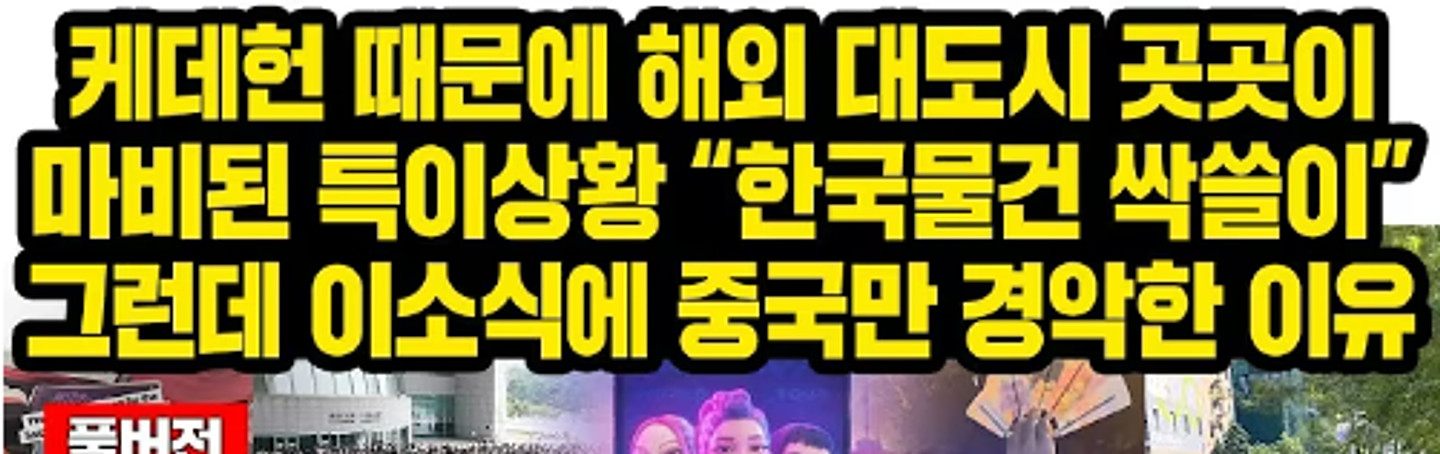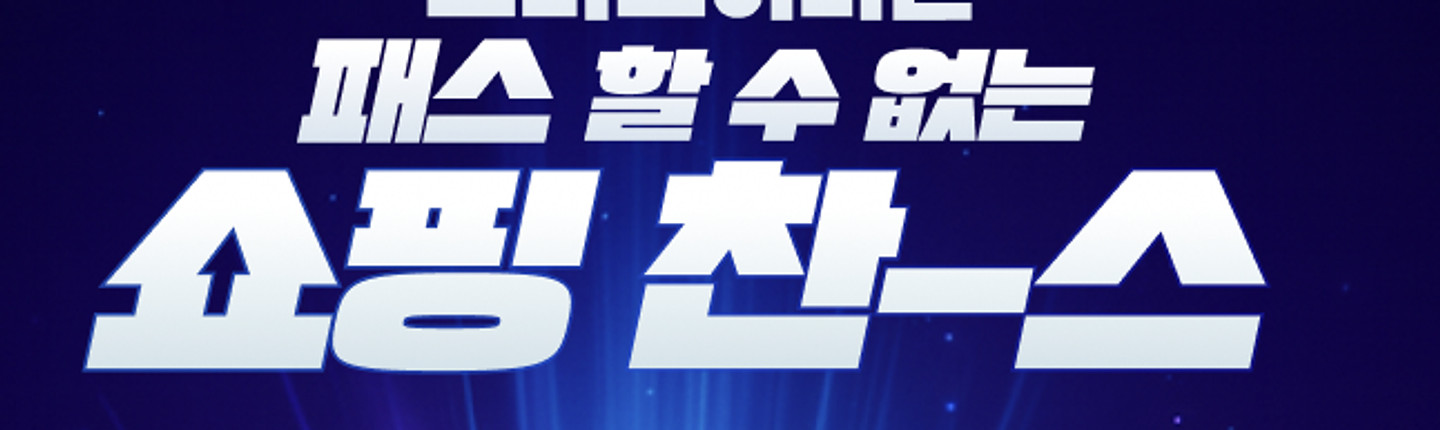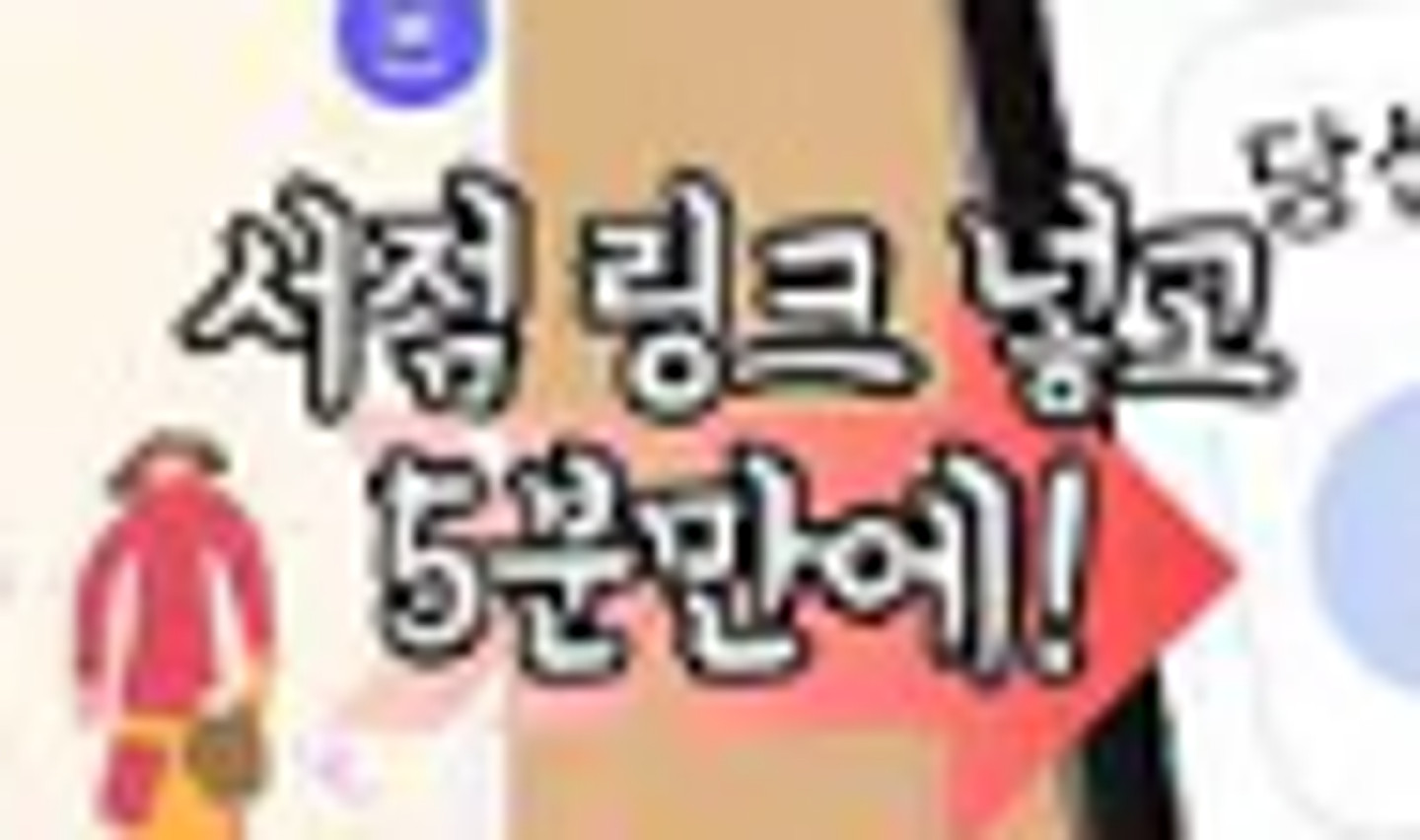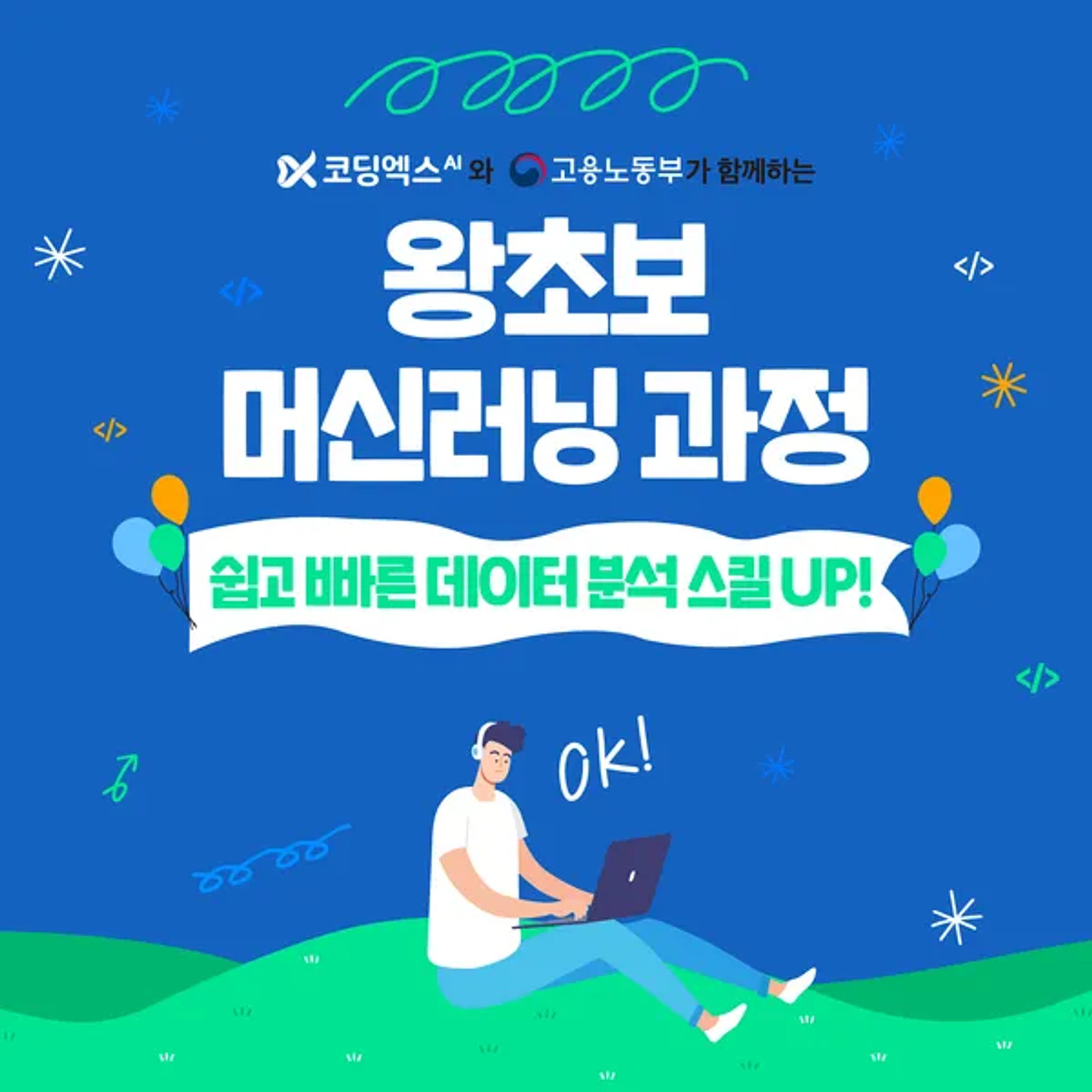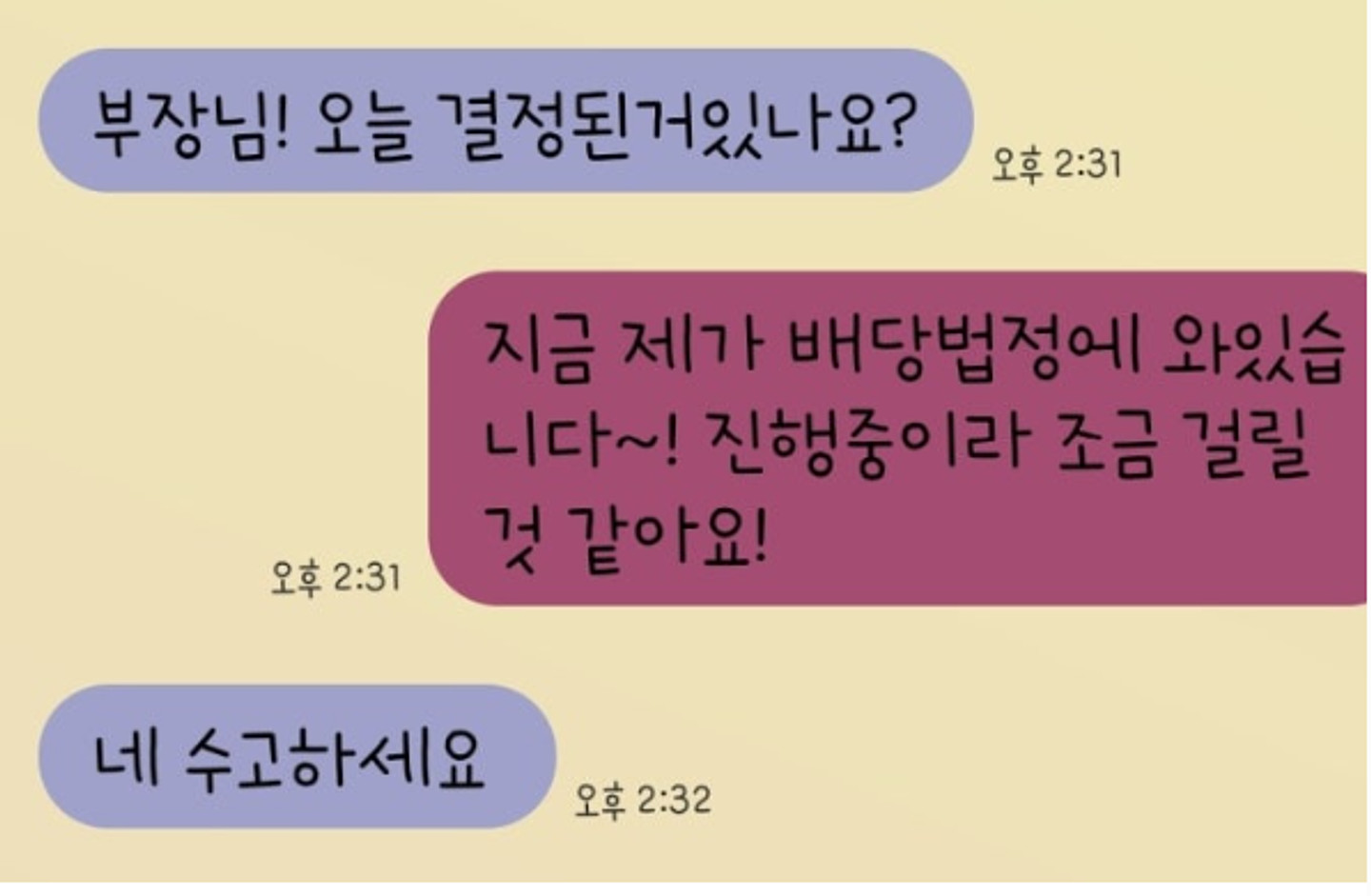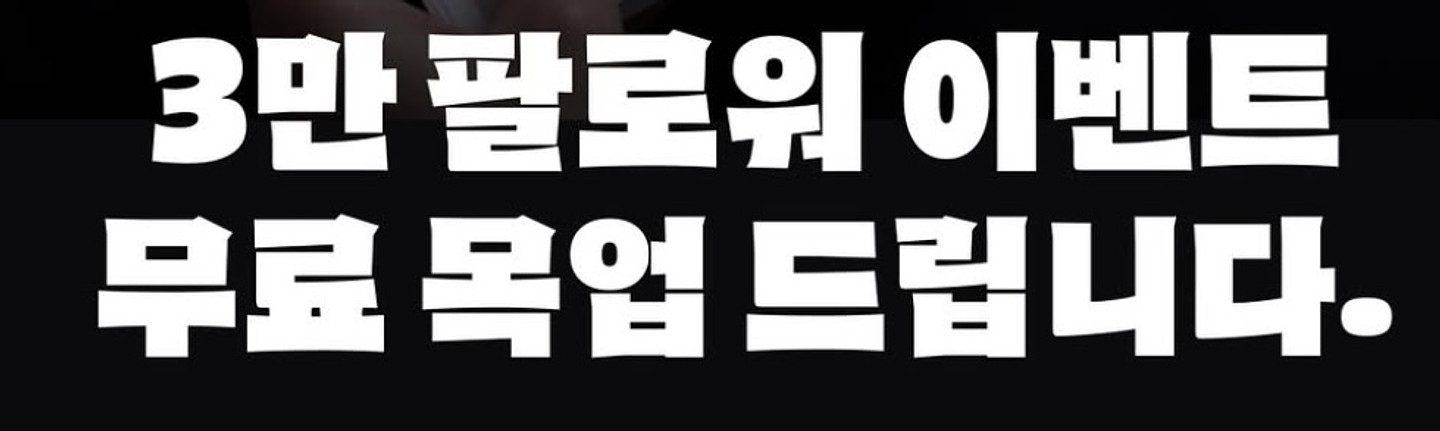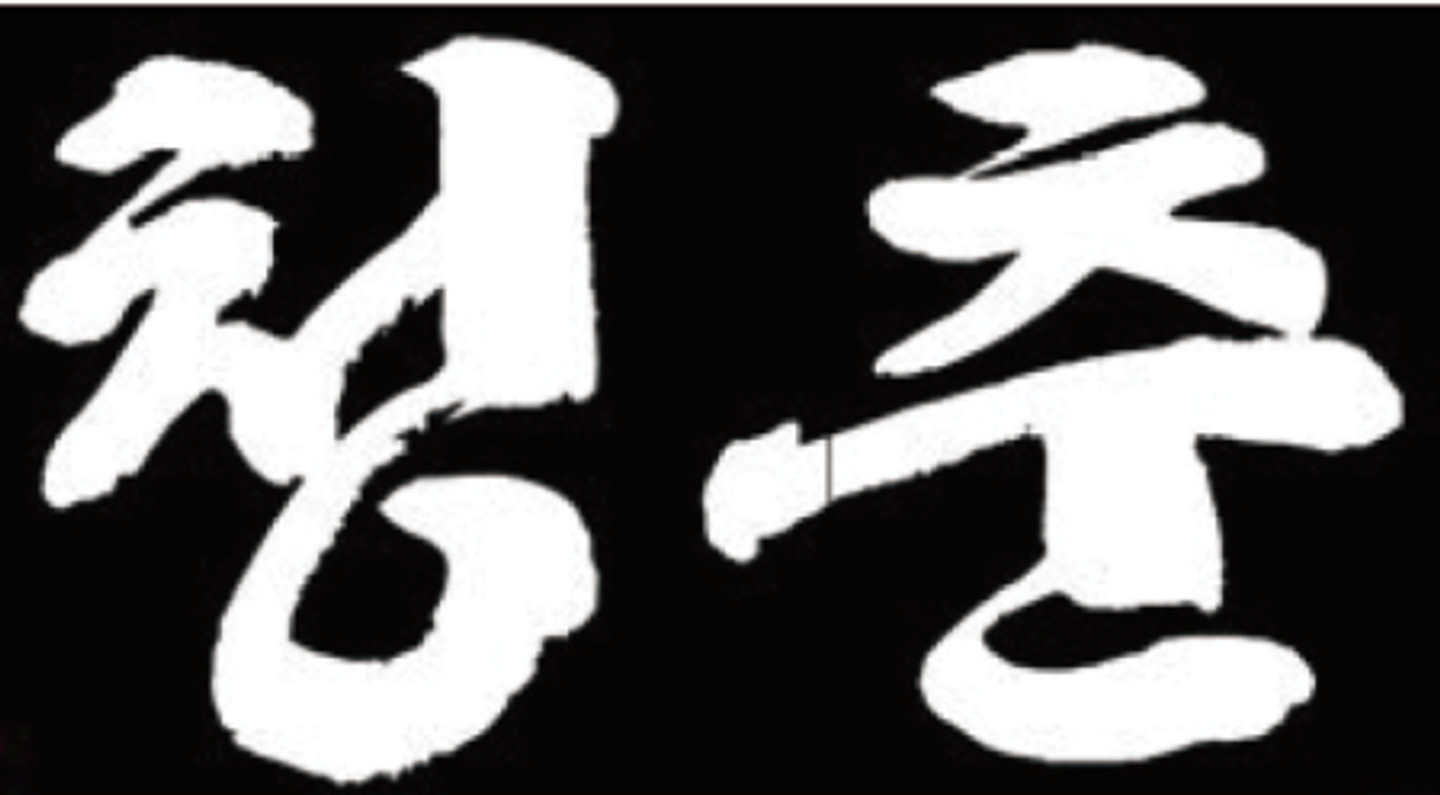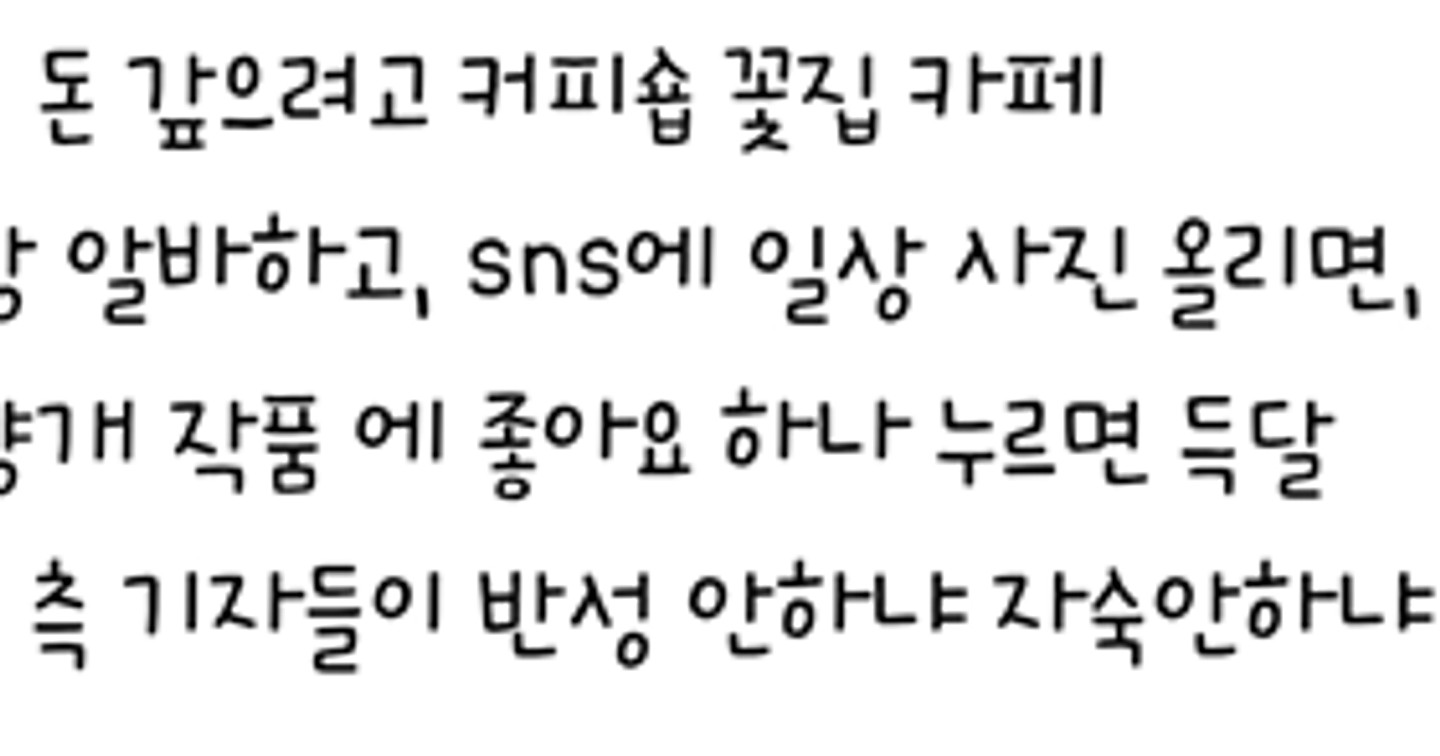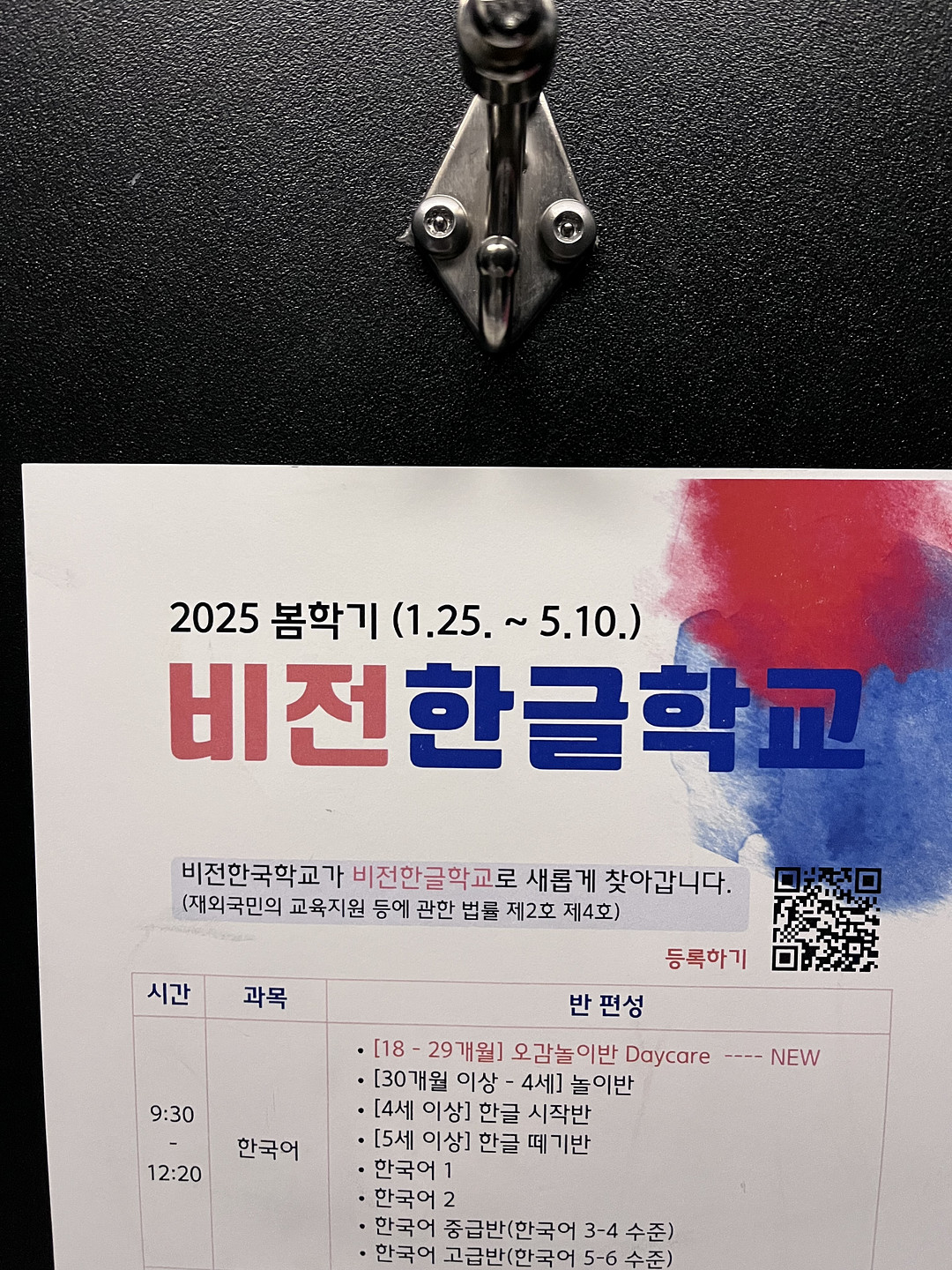
이거 폰트 무슨폰트일까요...???ㅠㅠㅠ
안녕하세요. 이 카톡 폰트를 쓰다가 날라갔는데 도저히 못 찾겠습니다. 다른 폰트는 다 미묘하게 달라서 꼭 이걸 사용하고 싶은데 집단지성의 힘이 필요합니다 한번만 도와주세요..!
서체 알려주세요
이거 무슨 폰트 일까요??
이거 무슨 폰트일까요???
이 폰트는 무슨 폰트일까요? 너무 쓰고 싶습니다. ㅠㅠ
제발 이거좀 알려주세요ㅠㅠㅠㅠ
이 폰트의 주인을 찾숩니다..ㅠㅠ!!
ㅜㅜ
이거 알려주세요 ㅜㅜ
이 한자 무슨폰트인가요??
이거 무슨폰트인가요??
폰트가 뭔지 궁금해요...
폰트 정보를 알고 싶어요!
이거 무슨 폰트일까요~? 미리 감사드립니다!
ㅎ ,ㅈ , ㅁ 이 특이하게 생겼는데, 아무리 찾아봐도 무슨 폰트인지 모르겠어요. 갤럭시 스토어에도 없고..ㅠ_ㅠ 아시는 분!!!!
이거 무슨 폰트일까요?! 너무 찾고 싶은데 아무리 뒤져도 모르겠어요ㅠㅠ
이거 무슨 폰트인지 아시는 분 계실까요...?
what's on my desk폰트뭘까요?
산리오 상세페이지에 있던 뚱뚱이 폰트 뭔지 알려주세여
혹시 이 폰트가 어떤 폰트인지 아시는 분 계실까요???ㅠㅠ 급하게 디자인 해야하는 작업이 있어서...ㅠㅠ
뭉게 구름 같은 이 폰트.. 대체 뭘까요 ?
폰트.... 뭘까요 너무 궁금해요 감사합니다
이거 글씨체가 멀까용?
유튜브 적수다에 나오는 이 썸네일 폰트 뭘까요?
릴스에서 본 폰트인데 무슨폰트인지 궁금합니다.
이 폰트 어떤걸까요???
귀여운 폰트
무슨 폰트야?
이 폰트 뭔지 궁금해요...!!
어떤 폰트인가요
이 폰트 이름 뭔지 알 수 있을까욧..?? ㅜㅜ
폰트폰트 사이트에서 검색해봤는데 KoreanPKSR Regular, WOOKS 스톤킹으로 형태가 너무 다른 것들만 뜨네요 무슨 폰트일까요?
글씨체좀 알려주세요 ㅜㅜㅠ
궁금해요 ㅜㅜ
이 폰트를 알고 싶어요~ 부탁드려요~
이거 무슨 폰트일까요 ㅠㅠ 비슷한 폰트라도 알려주시면 완전 감사합니다!!!!
철통닭갈비 이 서체 이름 뭔가요¿
이거 무슨 폰트일까요 ㅠㅠㅠ 아무리 찾아도 안나와서 ..ㅠ
이 폰트는 무슨 폰트일까요? 궁금해요ㅠ
썸네일 큰 글자들 무슨 폰트인가요??
이거무슨폰트인가요?
혹시 어떤 글씨체 일까요?ㅜㅜ
이 폰트 궁금합니다!!
무슨 폰트 일까요 ?! ㅜㅜ
이 폰트는 뭔가요ㅠㅠ?
비슷한 폰투 찾고잇어여… 똑같은 거 말고 제발 무료엿으면 좋겟어요
답변 감사합니다ㅠㅠㅠㅠ 혹시 이폰트랑 비슷한 무료폰트는 없을까요?!
분홍색 제목이랑, 아래 숫자 부분이랑 둘다 폰트가 궁금합니다!!
뮤직뱅크 가사 폰트인데요 혹시 아시는분 계실까요... 편집해야되는데 필요해서요ㅠㅠㅠㅠㅠㅠ
사진 좀 흐려서 죄송합니다 sns 보다가 알고리즘으로 본 사진인데 폰트가 이뻐서 찾고있는데 혹시 무슨폰트인지 아시는 분 있울까요ㅠㅠ
폰트 뭘까유?
폰트 알려주세요.
숫자 폰트 알 수 있을까요
폰트가 궁금해요!
저 JJSKR 폰트 이름이 뭘까요?